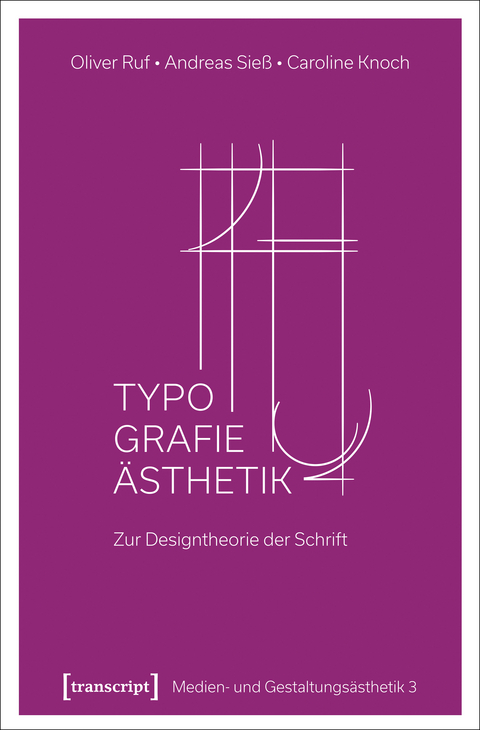
Typographie-Ästhetik
Die Gestaltung der Schrift, ihre Formgebung und Funktionszuweisung ist mit Hilfe ästhetischer Theoreme neu zu lesen.
Oliver Ruf, Andreas Sieß und Caroline Knoch zeigen, dass diese Typographie-Ästhetik eine Designtheorie bedingt, die immanent abhängig ist von gesellschaftlichen respektive kulturellen Faktoren, die Räume auf beiden Seiten erschließen: den Raum der Schrift (sowohl auf Papier/auf einem Bildschirm als auch im Setzkasten/in der Software) und den Raum der mit ihr affiziertem Artefakte (Produkte/Gegenstände). Damit werden neben den Möglichkeiten einer visuellen Koexistenz von heterogenen Zeichensätzen auch jene Anforderungen fixierbar, die die Annäherung differenter Kulturen und Gesellschaften immer schon mit sich führt.